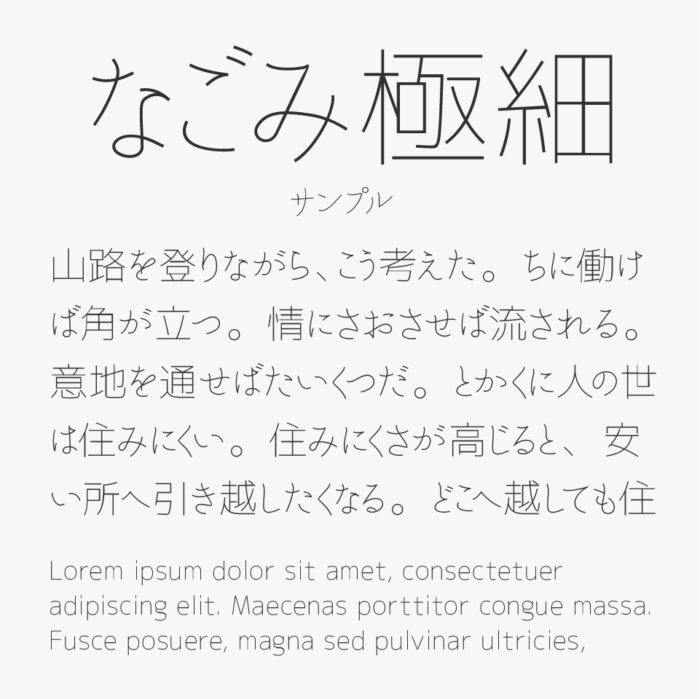
なごみ極細ゴシックフォントは、モダンで直線的な文字デザイン、それとは対照的に懐が狭くオールドスタイルなかな文字デザイン、二つの特徴が合わさったユニークな日本語フォントです。
なかなかここまでの細めのゴシックフォントで、フリーフォントはないので、超極細なウェイトになっているので、スタイリッシュな細いウェイトの文字を探している方にはオススメのフォントです。
収録文字は、かな文字以外の文字グリフを、オープンソースであるM+ フォントで補っているとのことでしたので、通常に使う限りでは問題ないかと思います。